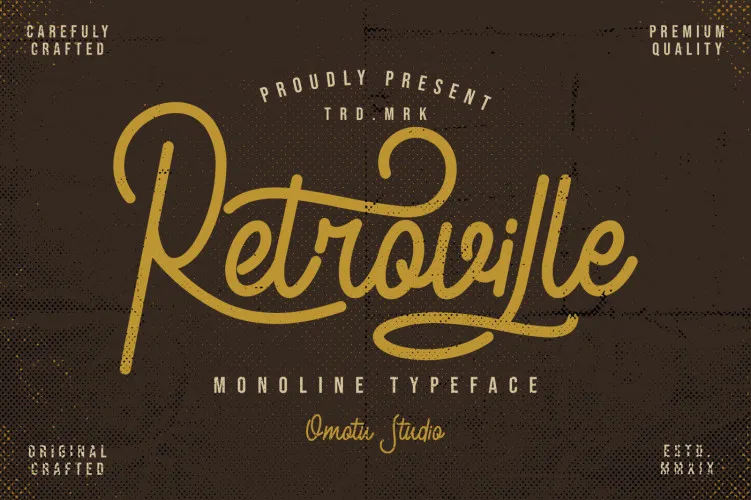
Retroville Script Font é uma nova fonte vintage criada para quem procura algo que seja mais do que apenas legível. Este bold script se destaca dos outros graças a combinações únicas e belas, perfeitamente adaptadas à moda moderna de rótulos e logotipos. Através deste estilo, você verá Retroville Script Font mais frequentemente em elementos como rótulos, selos ou logos, prometendo uma experiência de tipografia inovadora. A fonte Retoville Script é um tipo monoline com um estilo semi-sigurário. Seu uso irá transportar o usuário para um novo mundo na escrita e impressão. É perfeitamente adequado tanto para logotipos quanto para headlines, roupas, citações ou até mesmo para criação de posters vintage e exclusivos. Com Retroville Script Font em sua coleção de fontes, você pode revolucionar a maneira como seus materiais são apresentados, oferecendo um toque autêntico que combina modernidade e sofisticação. Engane-se: não é apenas uma nova fonte, mas parte integrante de um novo design visual que trará vida para seu trabalho.